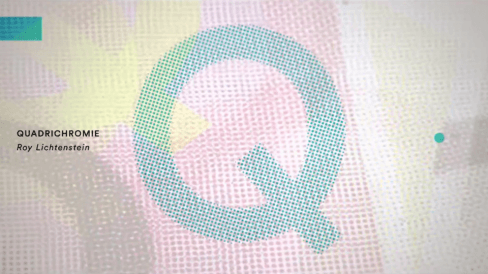
Uma homenagem a grandes artistas plásticos que une animação, tipografia e texturas
O designer gráfico francês Alex Zacchi criou uma animação visualmente impressionante para homenagear diversos artistas plásticos clássicos e contemporâneos.
Através da tipografia, ele usa as texturas características de cada artista e cita mestres como Roy Lichtenstein
, famoso por suas obras em quadricromia inspiradas na linguagem das histórias em quadrinhos. O resultado é um vídeo fantástico, com as intrincadas texturas mostradas de A a Z (em francês).